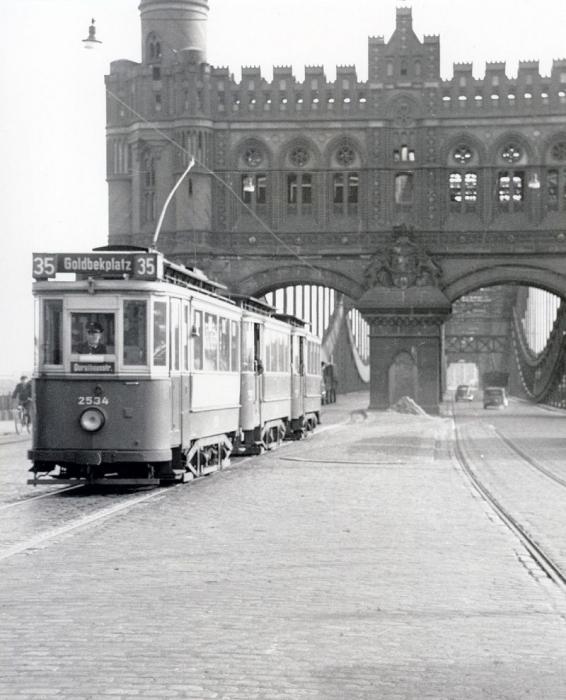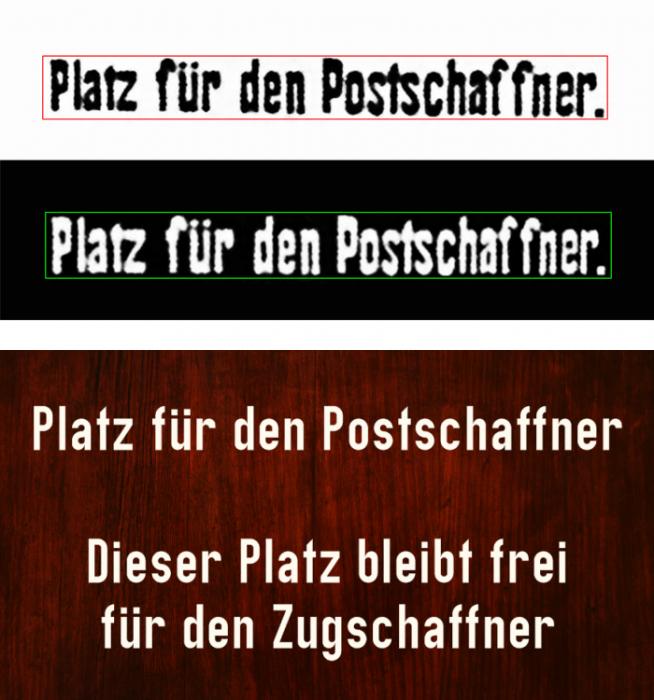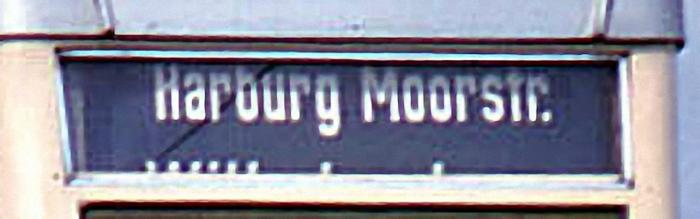
Jugendstil-Beschriftung aus Berliner U-Bahn, 1908
Alex in der Tat, sieht sehr ähnlich aus.
Wenn du Kontakt zu diesen Verein bekommst der sich mit diesen Strassenbahnen befasst und nicht den Namen der Schrift in Erfahrung bringen kannst, dann Frage mal ob du von den Zugzielen Fotos bekommst. Abmessungen der Buchstaben etc wären auch nicht schlecht. zur Not würden schon Refferenzobjekte reichen (Plastikkarte, oder A5 Bogen mit cm-Maß oder was auch immer gerade verfügbar ist. Wenn fotografiert wird, darauf achten, dass keine Spiegelungen das Gesamtbild unbrachbar machen.
Wir hatten ja schon einmal ein ähnliches Projekt hier da ging es um Strassenschilder, wenn ich das noch recht in Erinnerung habe.
Stimmt, die schrift schaut der gesuchten wirklich ähnlich, die auffällige Überbetonung der waagerechten in der U-Bahn-Beschriftung könnte ja auch bein Foto-Fehler sein. Generell wurden ja solche "amtlichen" Texte oftmals gerade nicht in Zierschriften der Zeit, sondern möglichst "nüchtern" aber auf lesbarkeit achtend ausgeführt, während man in Museumswagen dann oft aus Ermangelung des Originals auf etwas Stilistischeres zurückgegriffren hat, was eigentlich gar nicht historisch ist. Ich könnte mir gut vorstellen, dass da durchaus etwas DIN-Ähnliches dahinter streckt, das durch irgend welche optischen Fehler bei der Aufnahme so schön Jugendstilig geworden sind.
Hier kommt auch die Dorotheenstraße dem ähnlich: post-22079-0-79763200-1455925789_thumb.j
oft sind doch solche Beschriftungen auch direkt hingepinselt worden – jeder »Beschrifter« hatte seinen eigenen Stil. Ich denke eine 100% passende Schriftart wird man nicht finden.
Die auf der Straßenbahn (im Zugzielanzeiger) sieht aber schon sehr gut aus – evtl. schaffst du es ja an unverzerrte Fotos von anderen Endhaltestellen zu kommen und die Schrift dann für deinen Zweck zu digitalisieren.
Nun, die Schrift der Straßenbahn-Zielrollen bei der Hamburger Hochbahn AG, deren Tochter ja die FFG sind verwendete sie 1950er Variante der DIN 1451, wie auch für alle weiteren Anschriften an den Straßenbahnwagen.
Diese Schrift ist ja direkter Nachkomme einer anderen Schriftart, der 1906 von der preußischen Eisenbahnverwaltung eingeführte Schriftart nach der Musterzeichnung IV 44 Ausagabe 3, welche bis 1923 für alle Bahnen in Preußen - und dan n dem Deutschen Reich bis 1023 für Anschriften verwendet, und dann durch die Überarbeitung als DIN 1451 ersetzt wurde.
In der Schriftart, die damals Eisenbahnnorm war, und auch der der FFG-Zielanzeigen entsprach, wie ich aus diversen Bildern der Hamburger Straßenbahn sehen konnte, hätten die Anschriften im Wagen so ausgesehen:
Im übrigen war auch damals schon der Siebdruck eine Option bei vielfach auszuführenden Anschriften in Fahrzeugen des ÖPNV.
Ich habe ja auch nicht gesagt, dass dies die Schrift vom U-Bahn-Wagen ist, sondern annähernd die der Hamburger Straßenbahn-Zielbänder und anderer Beschrifdtungen dort.
Die im Wagen ist eine andere, an die wir aber über die vermutete Ähnlichkeit mit der Hamburger Schrift nicht weiter kommen - hier ist die Ähnlichkeit auch nur wieder durch eine Unschärfe entstanden.
Um diese aber auch nur halbwegs authentisch zeichnen zu könnebn, bräuchte man schon eine bessere Abbildung, sonst wird das eben etwas zwar historisierendes aber letztlich ein totaler Neuentwurf.
Ich bin schwer beeindruckt, von deinem Fachwissen, catfonts!
Leider hatte ich meine ganze Hoffnung momentan auf den Zielfilm aus Hamburg gelegt. Ich frage mich aber, ob die Ähnlichkeit mit der U-Bahn-Beschriftung tatsächlich lediglich aus einer Unschärfe besteht. Bei anderen Zielfilmen der Hamburger Straßenbahn glaube ich dir ohne irgendwelche Zweifel (http://images.fotocommunity.de/bilder/bus-nahverkehr/strassenbahnen/triebwagen-typ-v7e-der-hamburger-strassenbahn-62ca0bfe-9547-40b5-942b-c4dc0b56234b.jpg), aber beim oben verlinkten Bild?
Leider habe ich überhaupt keine Ahnung von der Hamburger Straßenbahn. Der Wagen im Bild wurde (laut Wikipedia) von Orenstein & Koppel gebaut, damit würde auch die Spur zur SEG/FFG verlaufen. ..oder man hat auf ein Rollband aus einem Ersatzteilspender-Fahrzeug zurückgegriffen, womit SEG/FFG u.U. wieder im Rennen wäre.
Ich bemühe mich ja auch schon darum, in einem Hamburger Nahverkehrsforum nachzufragen, wer etwas dazu weiß (als außenstehender so tief einzusteigen um verschiedene Rollbänder kennen zu können, kann kaum gelingen), aber da dauert selbst das Freischalten nach der Registrierung noch an.